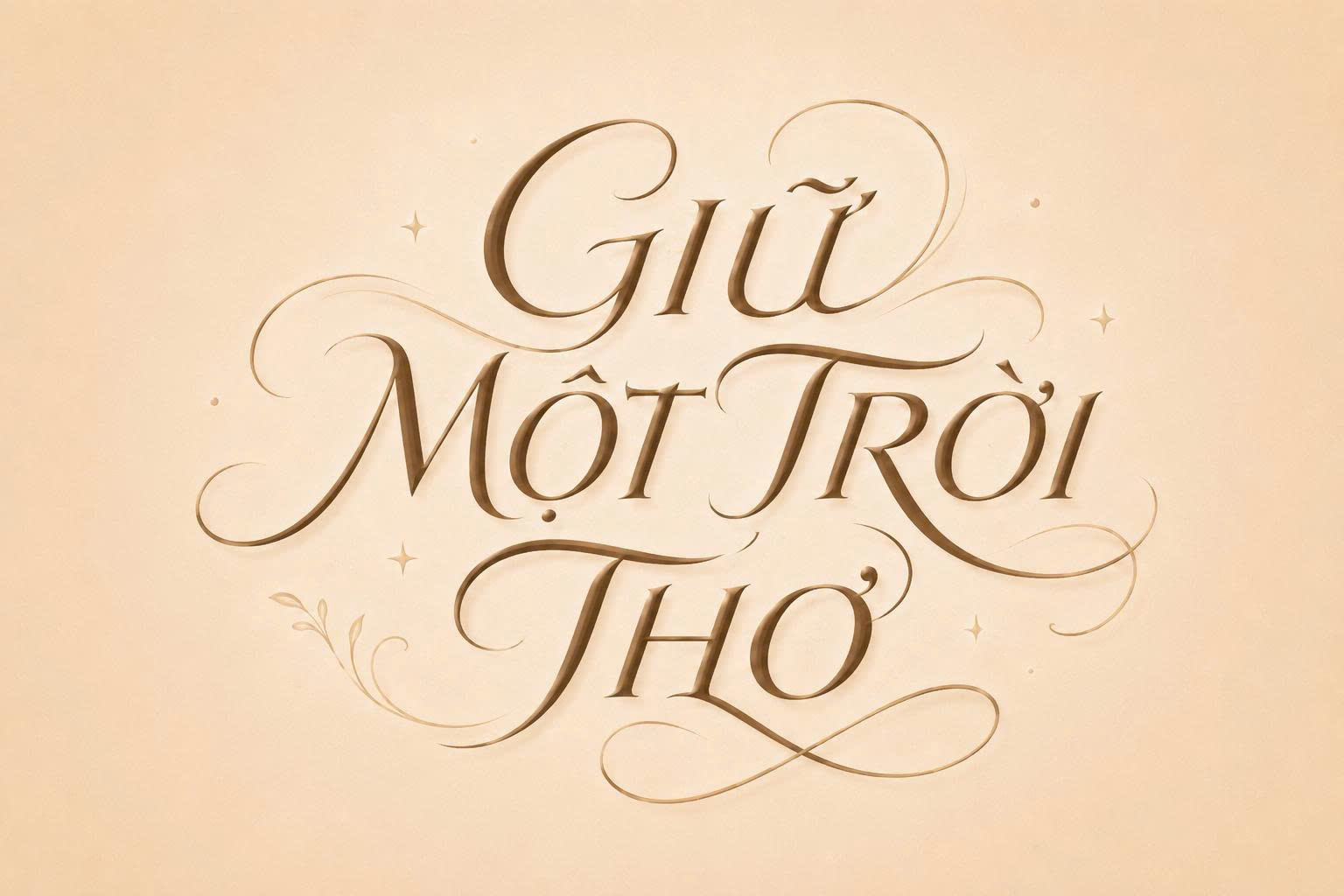
Font Calligraphy Việt hóa là dòng phông chữ nghệ thuật mô phỏng kỹ thuật viết tay bằng bút lông hoặc bút sắt với những đường nét uốn lượn, thanh đậm đan xen cực kỳ tinh tế. Khác với các font chữ thông thường, Calligraphy mang lại vẻ đẹp sang trọng, cổ điển và đậm chất cá nhân hóa cho bản thiết kế. Doozypack.vn chia sẻ link download font chữ calligraphy việt hóa chuẩn, đã được tinh chỉnh bộ dấu tiếng Việt giúp các designer và chủ shop tự do sáng tạo bao bì, thiệp mời mà không lo lỗi font.
Font chữ calligraphy viết tay Việt hóa là gì?
Calligraphy (nghệ thuật thư pháp hiện đại) là sự kết hợp giữa kỹ thuật đưa bút và thẩm mỹ hình khối. Một bộ font việt hoá calligraphy chất lượng phải giữ được linh hồn của nét vẽ tay truyền thống nhưng vẫn đảm bảo tính ứng dụng linh hoạt trên các nền tảng kỹ thuật số.
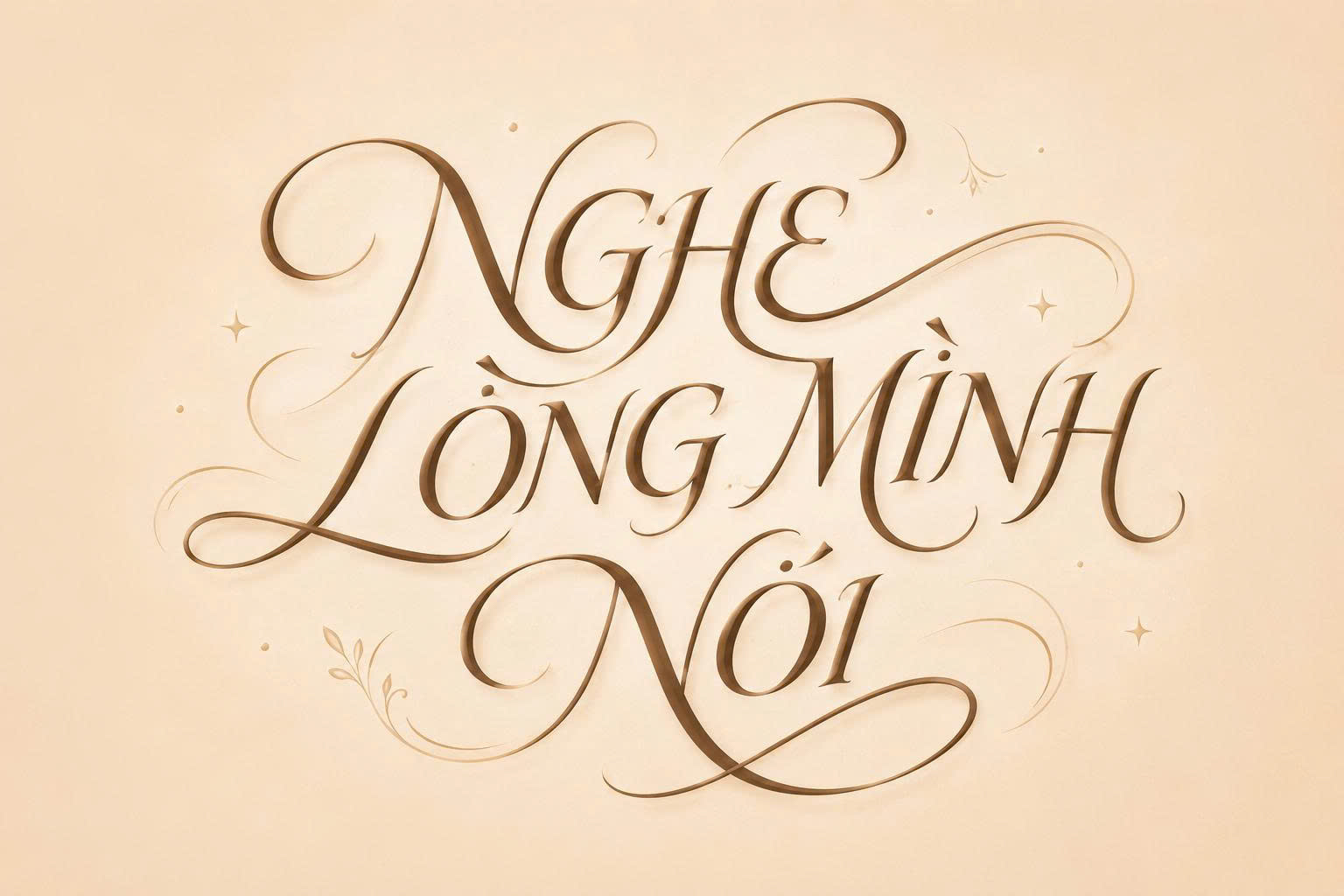
Đặc điểm thẩm mỹ: Sự kết hợp giữa nét thanh và nét đậm
Điểm nhận dạng đặc trưng nhất của các font chữ calligraphy việt hóa là sự tương phản mạnh mẽ giữa các nét đưa bút lên (nét thanh) và nét nhấn bút xuống (nét đậm). Những đường uốn lượn (swashes) ở đầu và cuối chữ cái tạo nên một dòng chảy văn bản mềm mại, giúp bản thiết kế trở nên nghệ thuật và cao cấp hơn rất nhiều so với các font chữ cứng nhắc.
Tính ứng dụng: Tạo cảm giác thủ công và sang trọng
Dòng font này thường được sử dụng khi thương hiệu muốn truyền tải thông điệp về sự tinh tế, tỉ mỉ hoặc tính độc bản. Calligraphy việt hóa đặc biệt hiệu quả trong các dự án về thiệp cưới, logo nhãn hàng cao cấp, bìa sách nghệ thuật hoặc các ấn phẩm truyền thông sự kiện trang trọng.
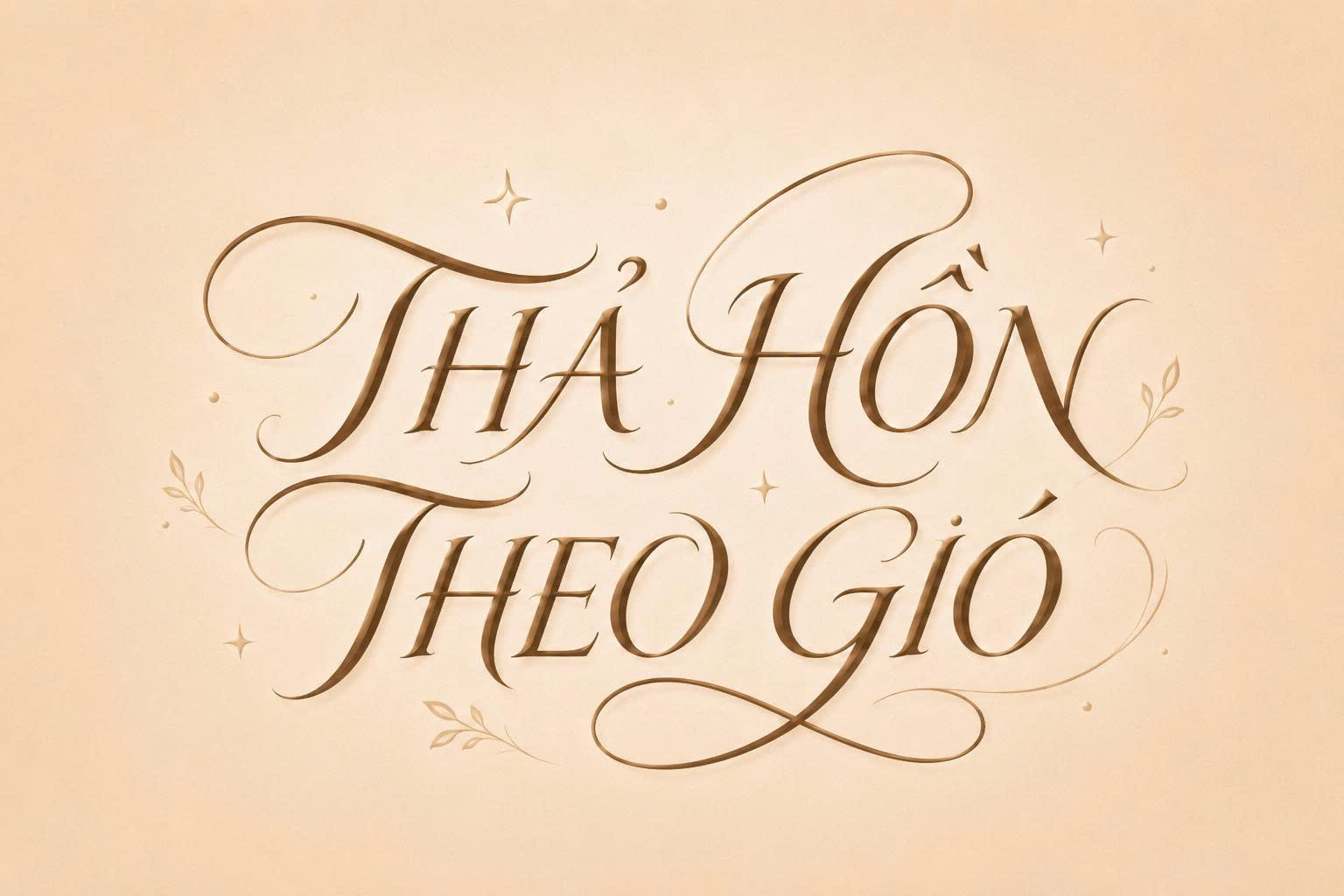
03 Ứng dụng của các font chữ calligraphy việt hóa trong thiết kế bao bì
- Hộp quà tặng cao cấp: Tên thương hiệu hoặc câu chúc bằng font Calligraphy in trên nắp hộp giấy cứng cán mờ tạo nên đẳng cấp vượt trội cho món quà.
- Thiệp và thư cảm ơn: Một chiếc thiệp cảm ơn (Thank you card) đặt trong hộp hàng với font chữ viết tay giúp khách hàng cảm nhận được sự chân thành của thương hiệu.
- Tem nhãn mỹ phẩm & nước hoa: Calligraphy mang lại vẻ đẹp thanh lịch, nữ tính, cực kỳ phù hợp cho các dòng sản phẩm làm đẹp cao cấp.
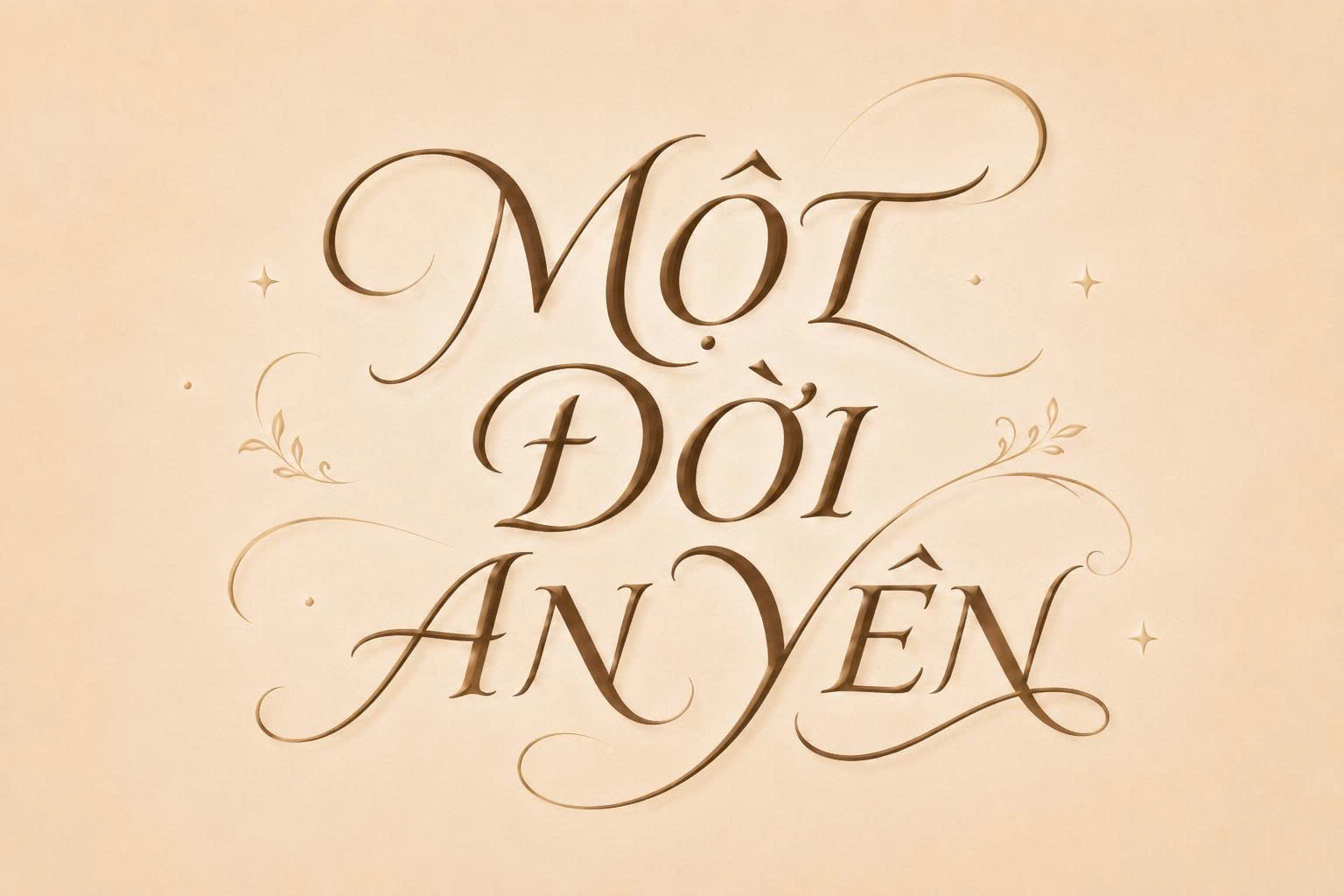
03 Lưu ý kỹ thuật khi đưa font việt hoá calligraphy vào in ấn thực tế
Việc in một bộ font có nét mảnh như Calligraphy đòi hỏi sự am hiểu sâu về quy trình sản xuất tại Doozypack.vn để tránh thành phẩm bị lỗi:
- Vấn đề ép kim (Gold Stamping): Font Calligraphy thường có các nét mảnh (hairline) cực nhỏ. Khi gia công ép kim, nếu nét quá mảnh sẽ không đủ diện tích để lớp nhũ bám vào, dẫn đến hiện tượng mất nét. Bạn nên yêu cầu xưởng in kiểm tra độ dày nét chữ trước khi làm khuôn.
- Xử lý khoảng cách dấu thanh: Trong font chữ calligraphy việt hóa, các dấu thanh đôi khi bị đè lên các nét uốn của chữ cái khác. Bạn nên điều chỉnh thủ công (kerning) để đảm bảo chữ rõ ràng, dễ đọc trên bản in.